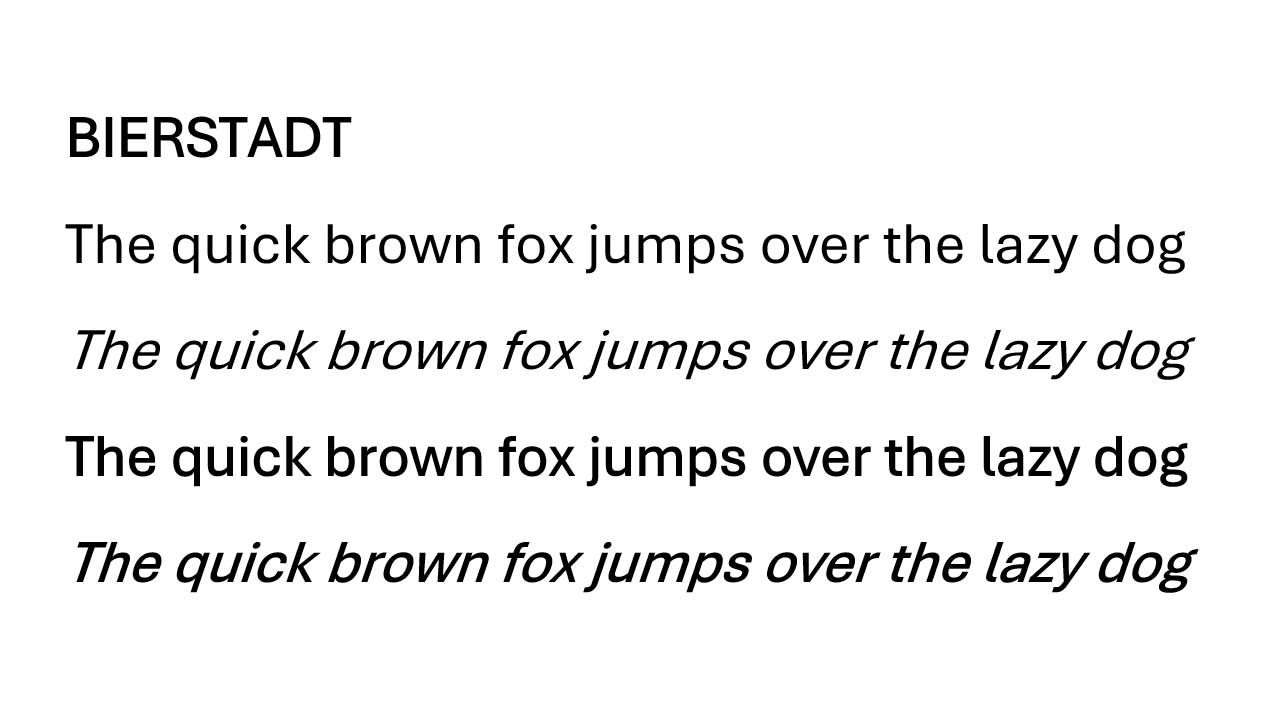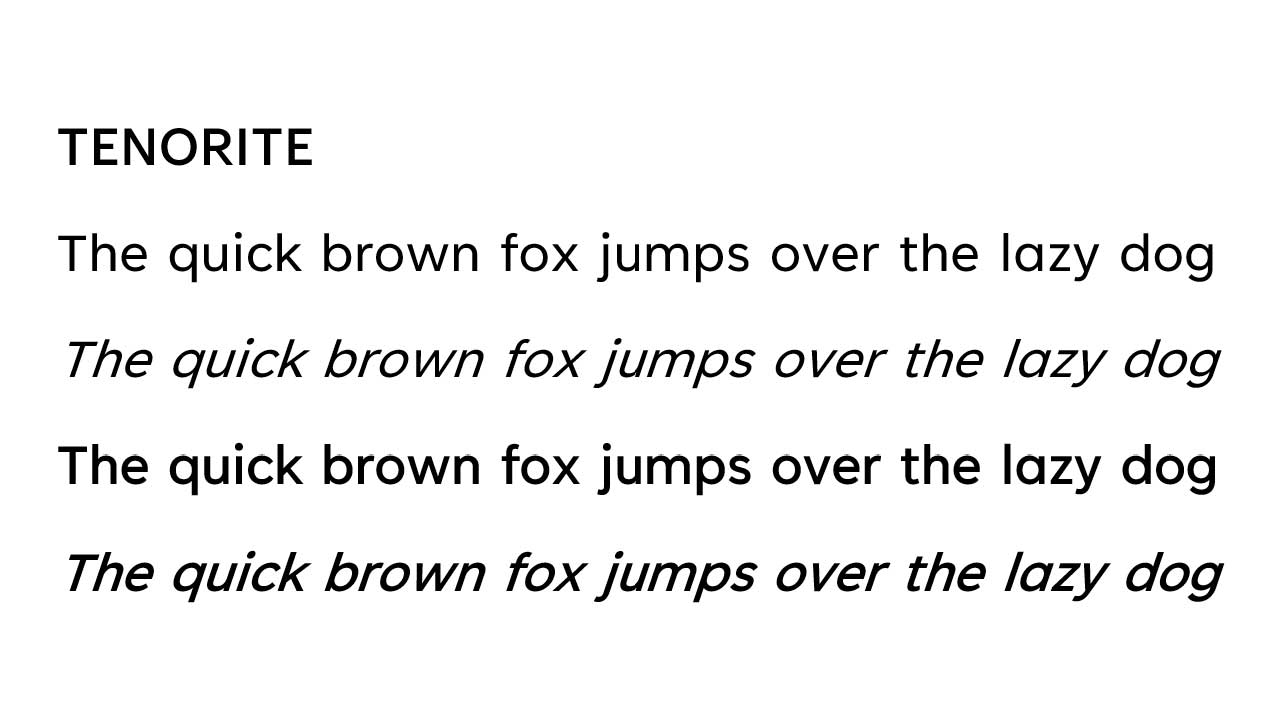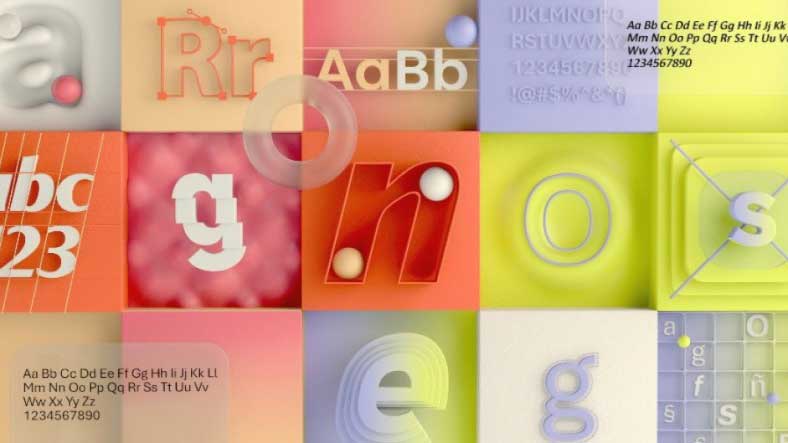
Wow, ini menarik. Microsoft berniat mengganti font utama di aplikasi Office dengan yang baru. Serunya lagi, mereka mengajak kita untuk ikut serta menentukannya.
Selama ini, font yang bernama Calibri sudah menjadi jenis huruf utama di aplikasi Microsoft Office. Font ini bisa kamu lihat ketika kamu membuat dokumen baru di aplikasi tersebut.
Calibri menggantikan huruf Times New Roman sejak Microsoft Office 2007. Jadi sudah lebih dari 10 tahun! Mungkin memang sudah saatnya berganti agar Microsoft Office lebih terasa fresh.
Kandidat Font Baru Office
Kini Microsoft mengumumkan 5 kandidat font baru, yaitu Tenorite, Bierstadt, Skeena, Seaford, dan Grandview. Kelima font ini termasuk dalam keluarga sans serif.
Jadi karakteristiknya lebih mirip Calibri. Berbeda tipe dengan huruf seperti Times New Roman yang punya tambahan garis di ujung-ujungnya (biasa disebut serif, sans berarti ‘tanpa’).
Walau sekilas kelihatan sama, jelas karakteristik tiap font berbeda. Mulai dari bentuk, jarak antar huruf, jarak antar kata, dll. Secara umum, kalimat khas “The quick brown fox jumps over the lazy dog” bisa memberi gambaran. Walau begitu, beberapa hal lain—seperti tanda baca—perlu teks yang lebih panjang.
Mencoba Font Baru
Nah, yang mana font favoritmu?